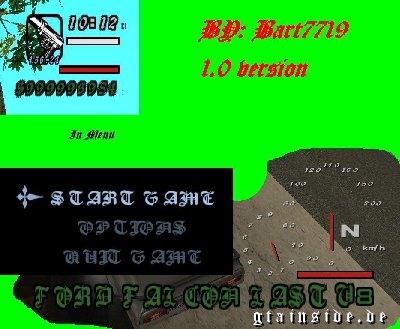
New font 1 0
Naja die fehler seh ich nich so wirklich außer das von "quit game" das "quit" unleserlich is, aber an sonsten find ich's klasse . Auch wen es nur umgetauscht is ^^ wenigstens macht sie hier eine darum mühe deshalb 9pkt. !!